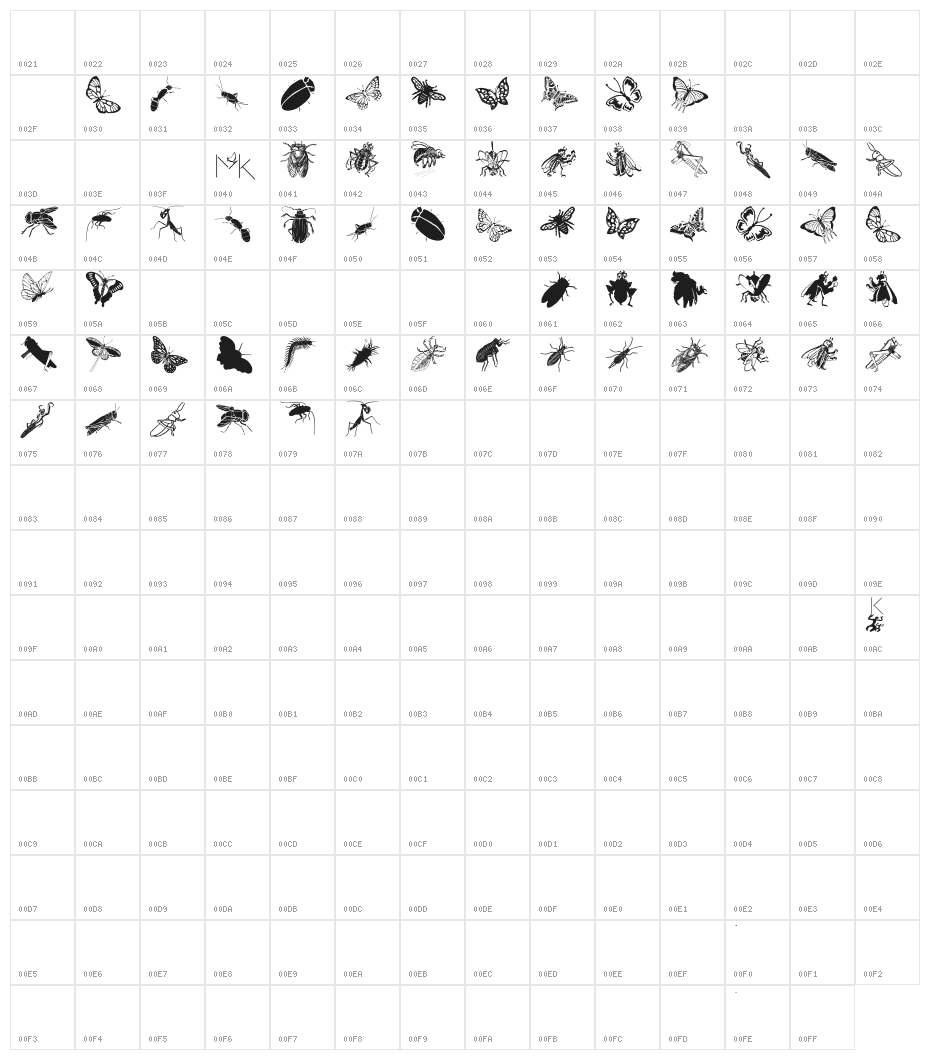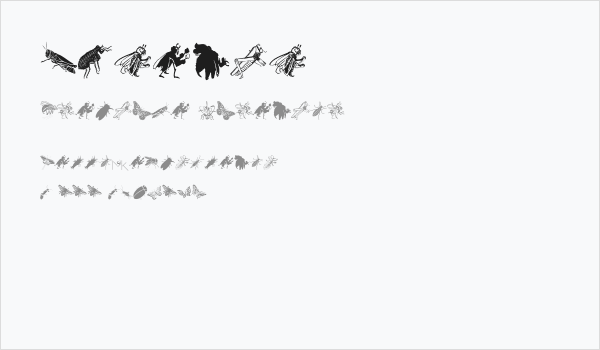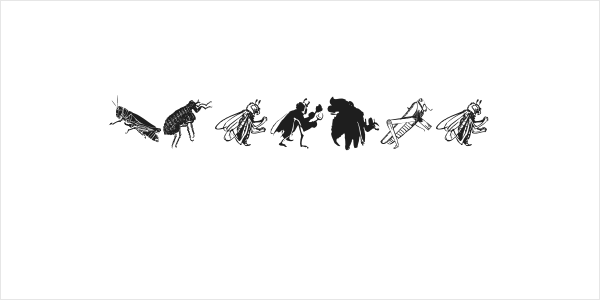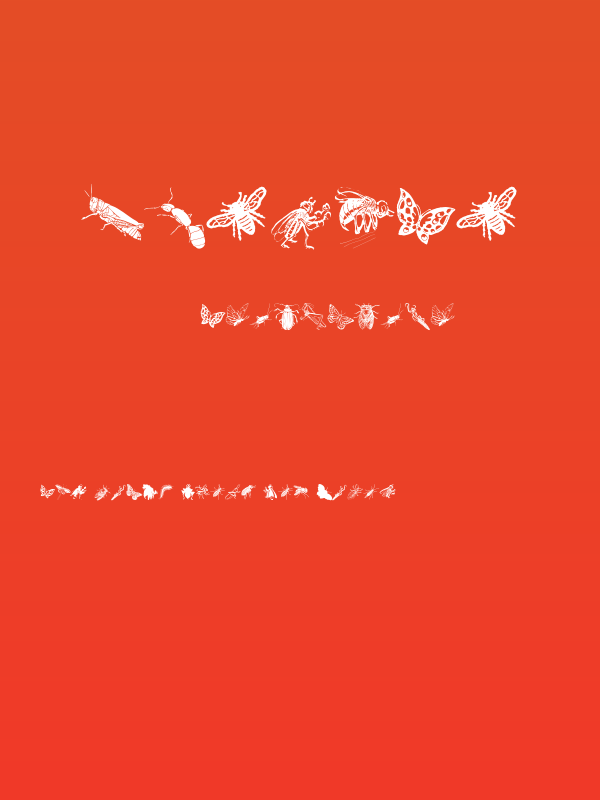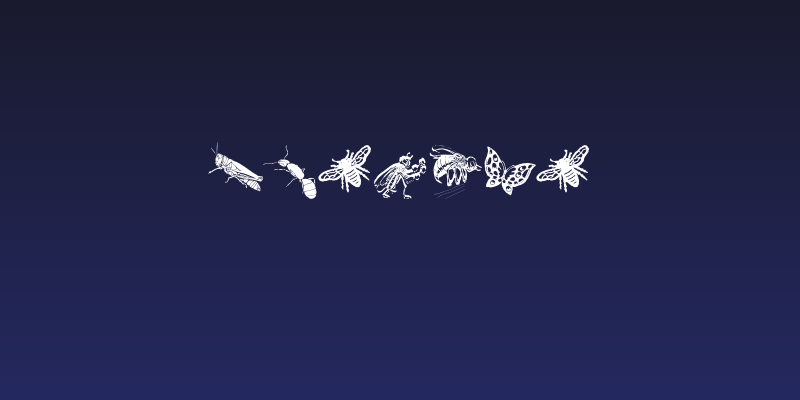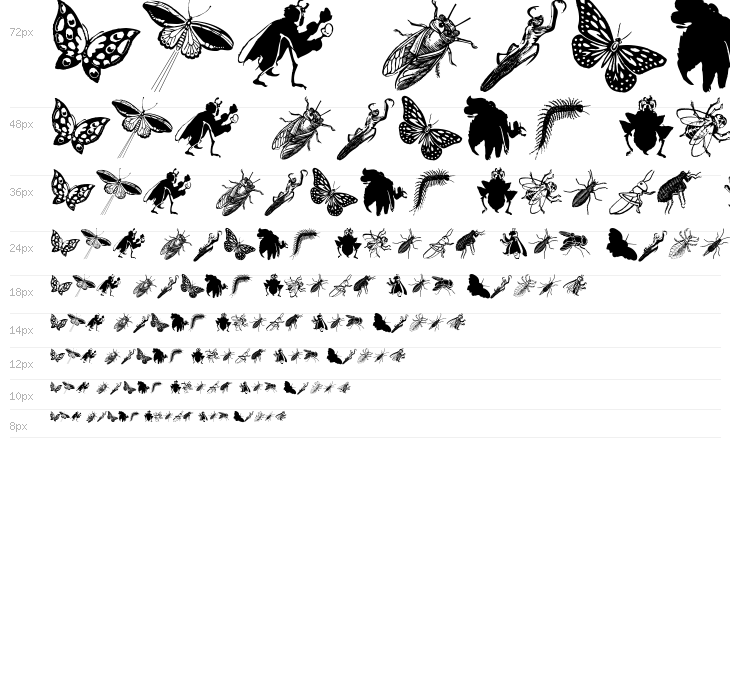
Insects Font
| Gesamtstil | Decorative, Nature-inspired, Illustrative |
| Anwendungsfall | Logos, Posters, Decorative headlines, Themed graphics |
| Vorgeschlagene Projekte | Educational posters, children's books, nature-themed invitations, science fair materials, creative branding for entomology or wildlife organizations. |